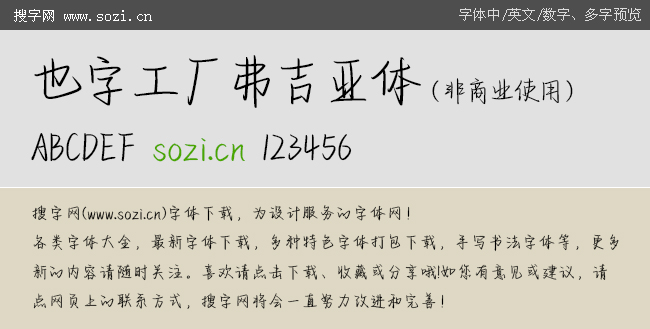
也字工廠弗吉亞體
搜字網給大家提供一款也字工廠弗吉亞體(非商業使用)中文字體下載,也字工廠弗吉亞體是一款手寫書法字體,字體書寫流暢自然,字形瀟灑大方。具有很好的視覺效果。適合應用于藝術設計、平面宣傳設計、網頁設計、海報設計等應用(此字體為個人非商用版,商用可以聯系:官方網址:https://yefont.com/home,聯系方式:13798980448)。